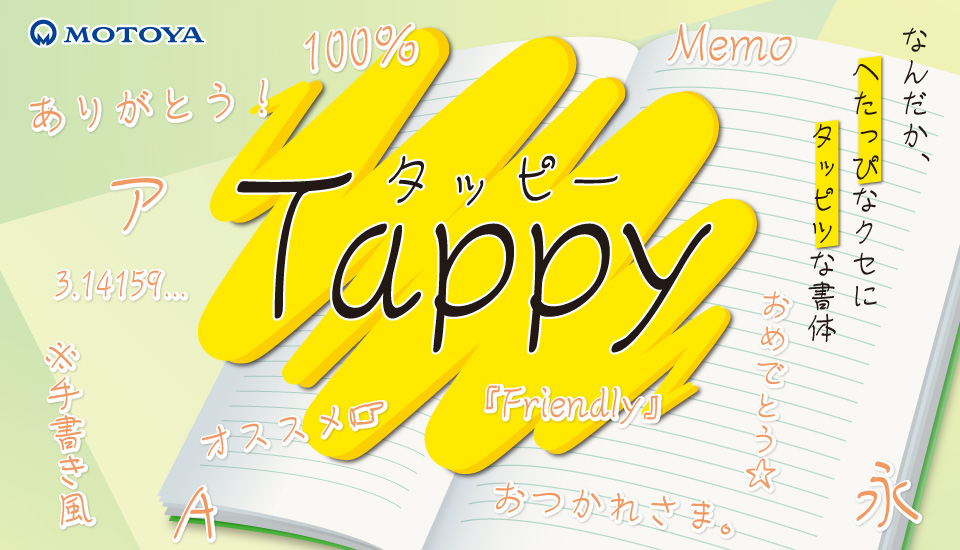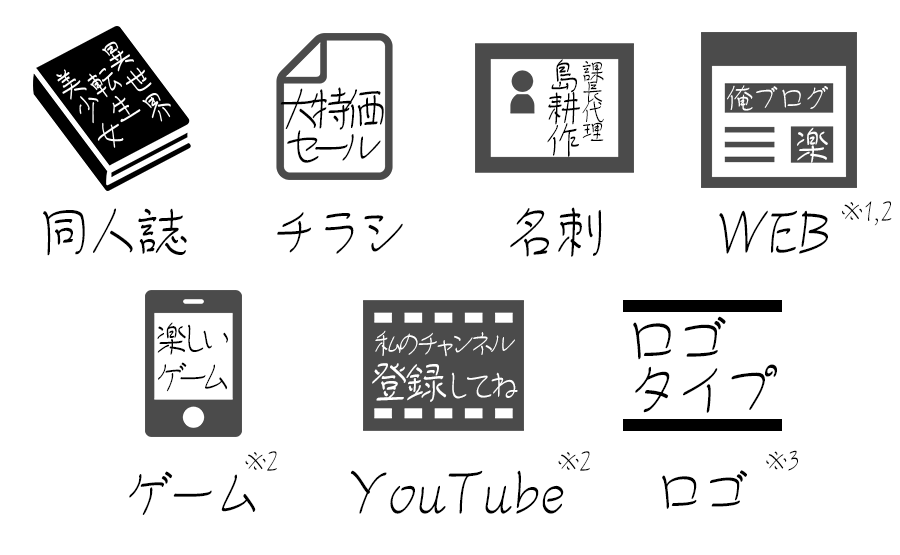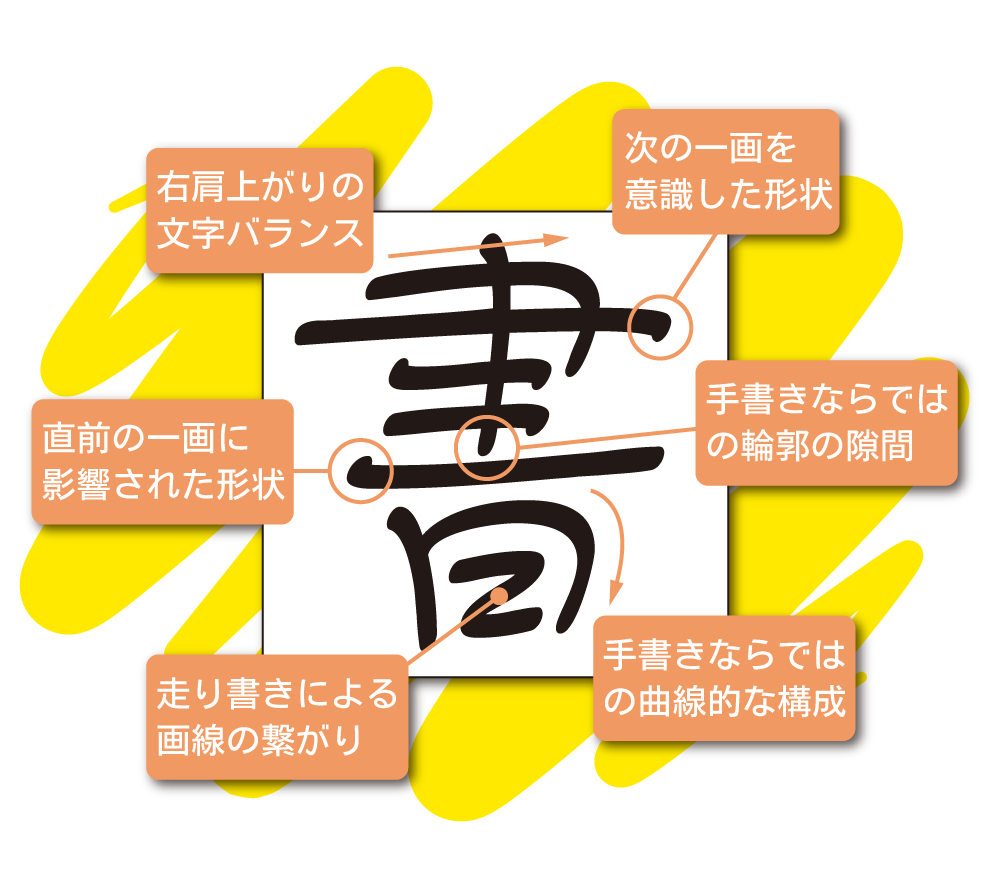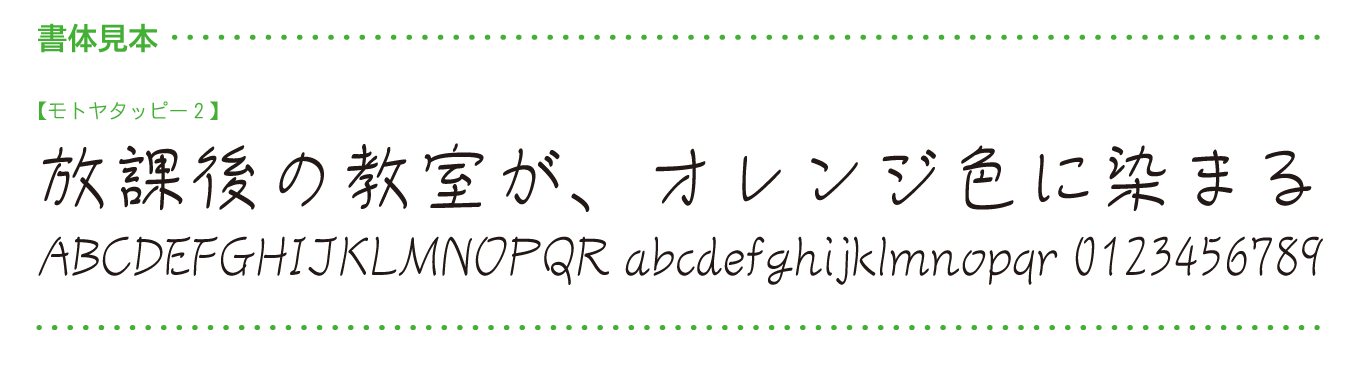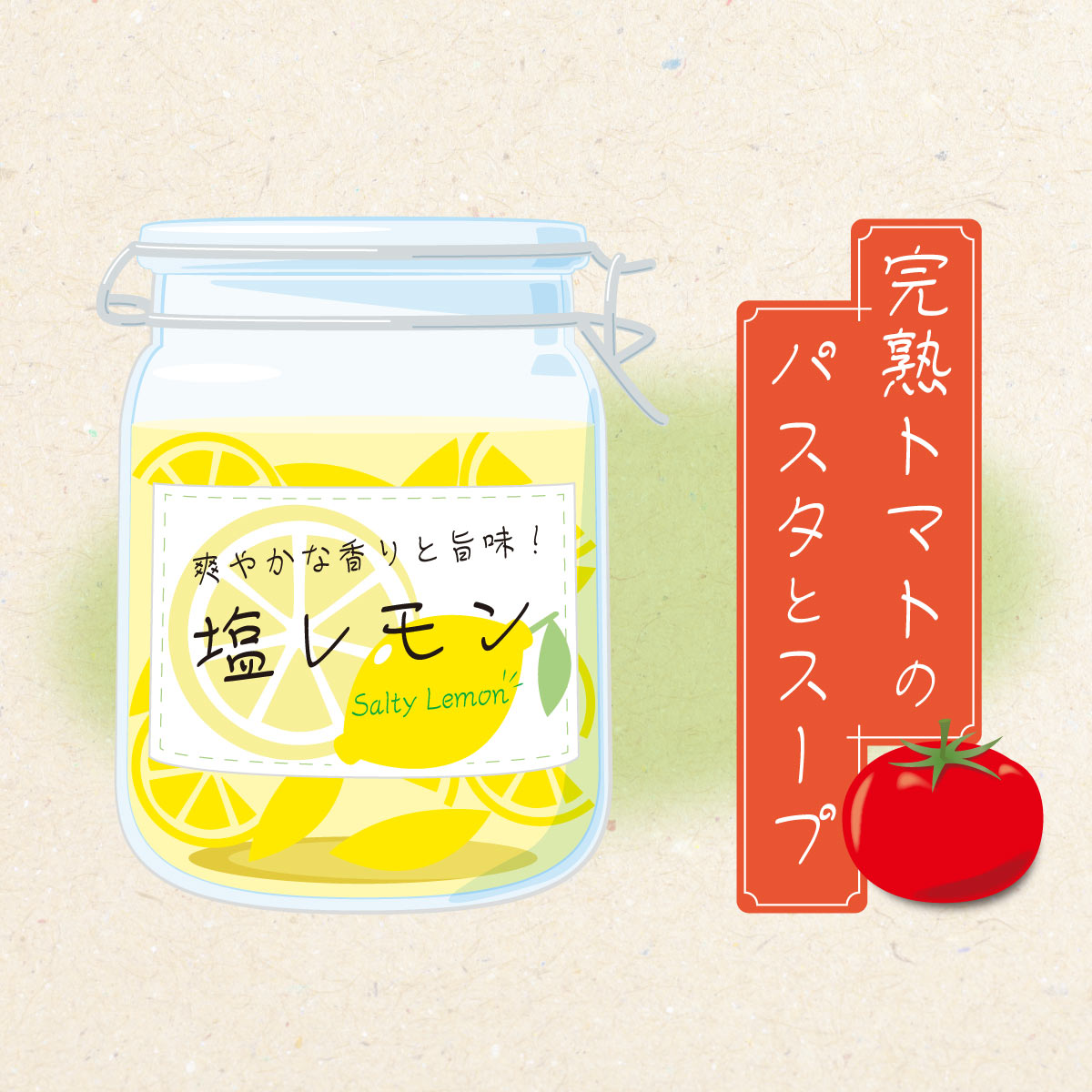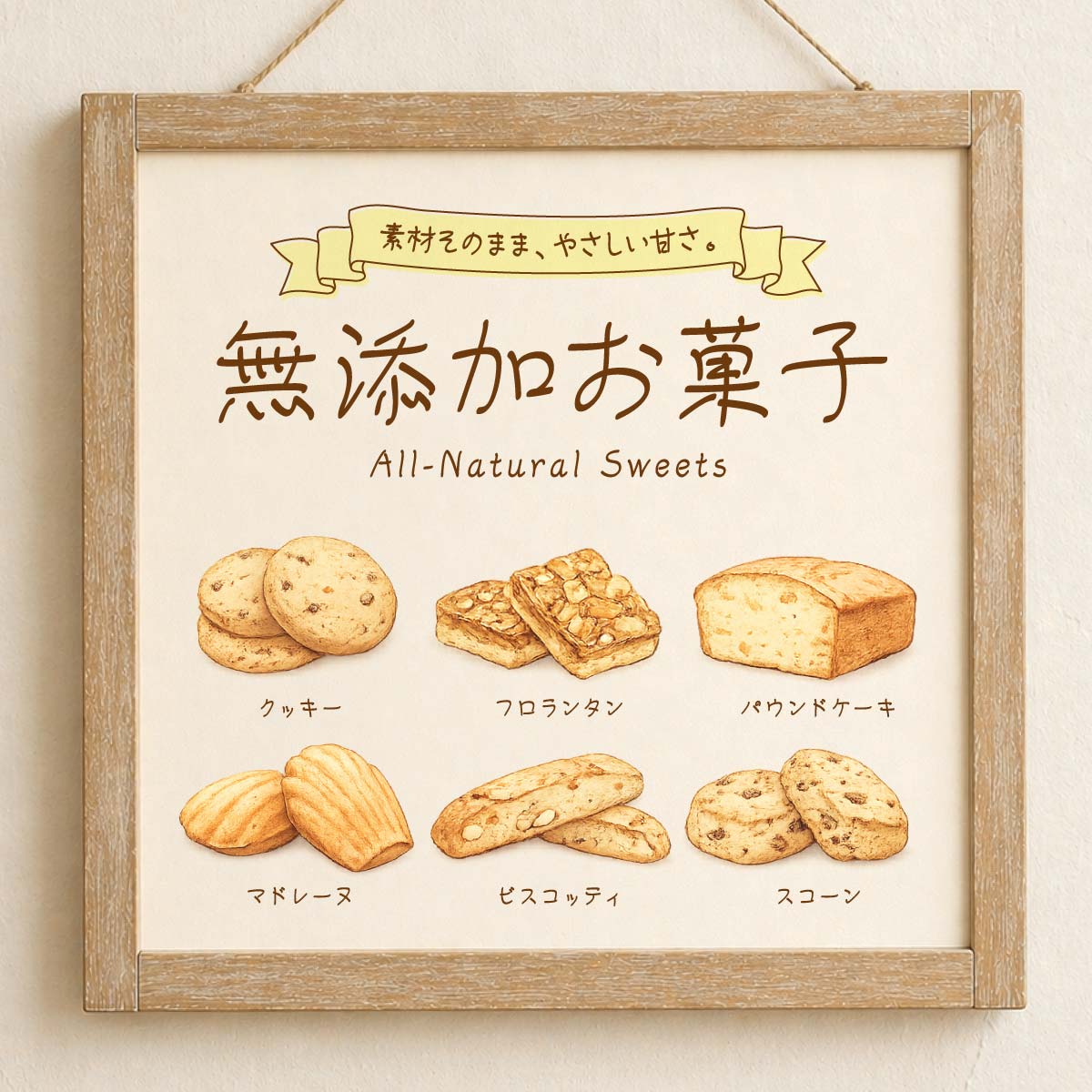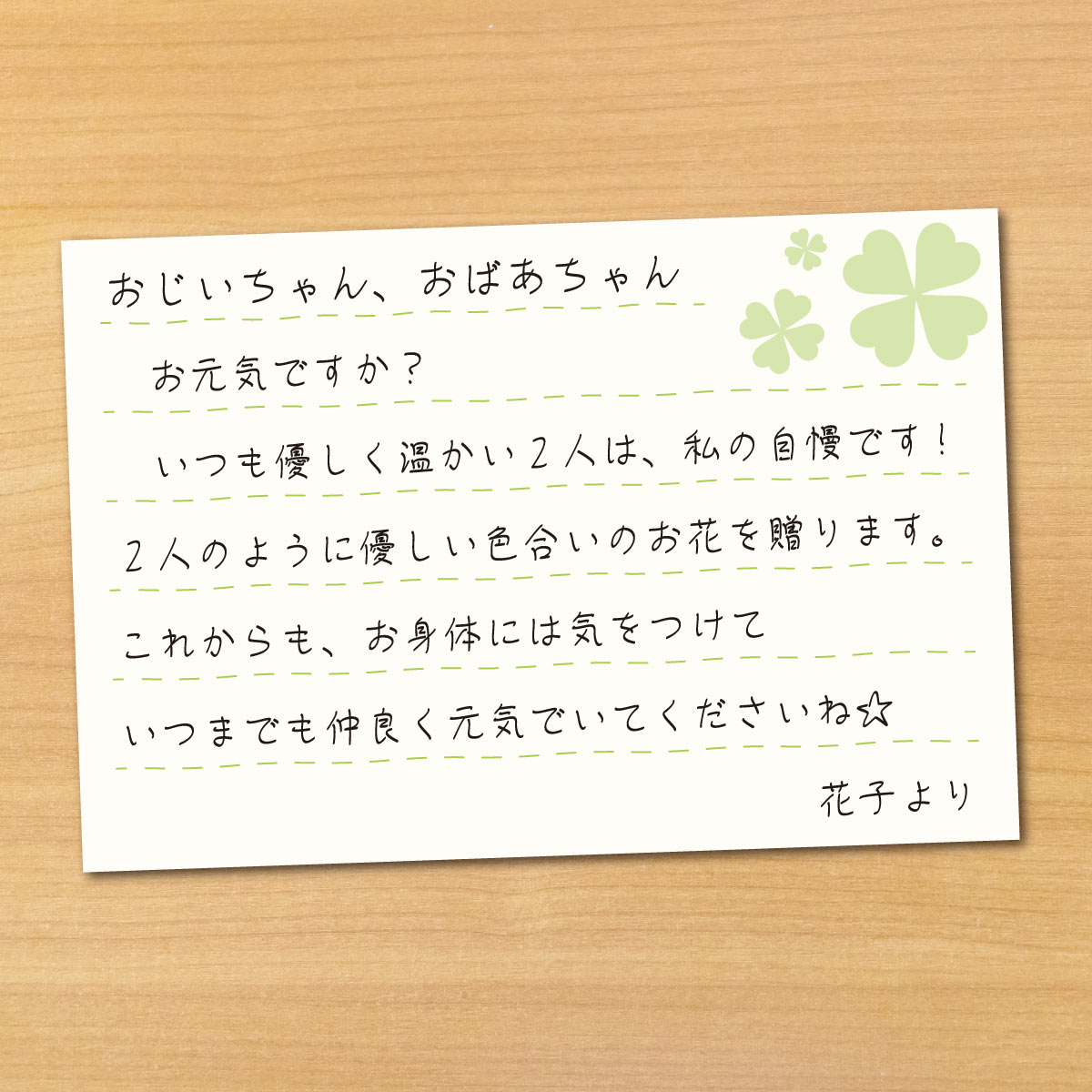
なんだか、へたっぴなクセにタッピツな書体 「モトヤタッピー」
ラフなのにフレンドリーな手書き風書体『モトヤタッピー』が登場!
なんだか、へたっぴなクセにタッピツな書体モトヤタッピー。ボールペンなどで少し急いで書いたような、書き崩れた文字が特徴の手書き風書体です。制作においては、クラスメイトから借りた授業ノートに書かれていそうな「ラフだけど親しみやすい」「上手すぎず、下手すぎない」「整っていないけど読める」、そんな身近な文字を目指しました。
モトヤタッピーとは
ボールペンなどで少し急いで書いたような、書き崩れた文字が特徴の手書き風書体です。制作においては、クラスメイトから借りた授業ノートに書かれていそうな「ラフだけど親しみやすい」「上手すぎず、下手すぎない」「整っていないけど読める」、そんな身近な文字を目指しました。書体名は、「下手(へた)っぴ」でもあり「達筆(たっぴつ)」でもあることから「タッピー」と名付けました。
書体の特徴
モトヤタッピーは、急いで書いたことによる勢いで、横方向の画線は少し右肩上がりとなっています。また、一画を書き終えて次の一画へ移る際に、少し早めにペンを浮かせたことで生じる画線の隙間や、短い画線が連続する時にそのまま続けて次の一画に移ったことで生じる画線の繋がり、曲線的な画線が多くなってしまうフリーハンド特有の部分など、「癖字(くせじ)」を文字デザインとして落とし込んでいます。